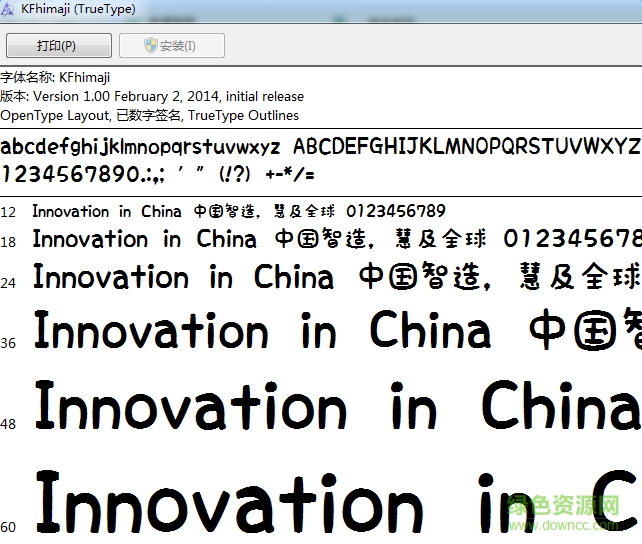
咕嚕萌萌體
咕嚕萌萌體字體是一款超好用的個(gè)性中文字體,該字體可以廣泛應(yīng)用于廣告設(shè)計(jì)、宣傳海報(bào)、ppt、影視制作以及任何使用文字的領(lǐng)域,有需要的朋友可以免費(fèi)下載收藏。
咕嚕萌萌體字體是一款極具個(gè)性的字體,該字體十分飄逸,彰顯了自己的個(gè)性,有喜歡的朋友可以來綠色資源網(wǎng)下載使用!